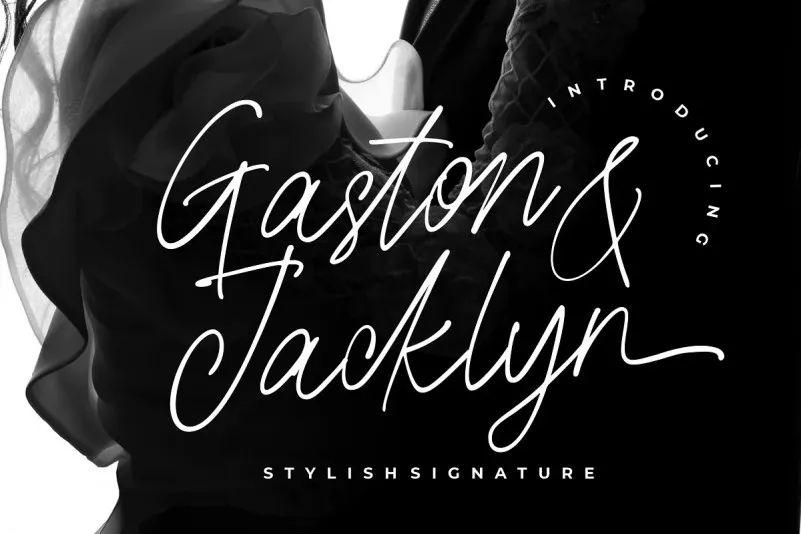
Aqui está uma descrição para a página de download da fonte ‘Gaston & Jacklyn Font’, adaptada ao formato solicitado: Uma fonte elegante e moderna, ‘Gaston & Jacklyn Font’ é perfeita para um design que valoriza o estilo pessoal. Este script oferece uma aparição descomplicada, com alternativas e ligaturas para adicionar a característica mais autêntica ao seu trabalho. É ótimo para criar marcas de negócios, criação de logotipos, designs de casamento, posts nas redes sociais, anúncios, embalagens de produto, desenhos de produto, etiquetas, fotografias, rótulos, convites e materiais de endereço. Suas alternativas e ligaturas permitem criar uma sensação de autenticidade que combina bem com a natureza informal da fonte. Este é um recurso para designers gráficos buscando adicionar personalidade aos seus projetos sem comprometer o profissionalismo. Com ‘Gaston & Jacklyn Font’, você pode escolher entre várias variantes do mesmo estilo, garantindo que todos os elementos de sua página ou projeto apresentem uma coerência visível e elegante.